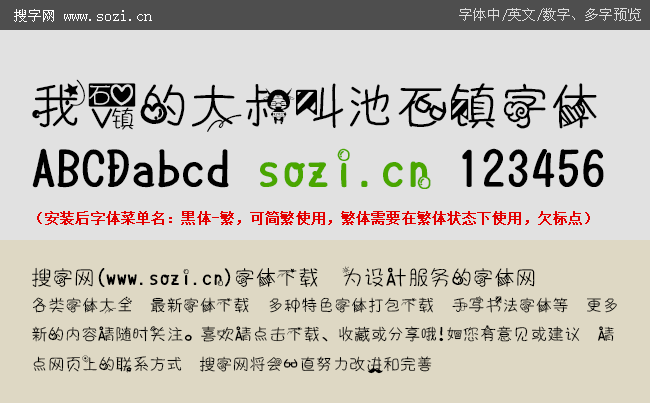
我愛的大叔叫池石鎮(zhèn)字體
搜字網(wǎng)給大家提供一款很卡通的手寫風(fēng)格手機中文字體下載。修改者將它命名為我愛的大叔叫池石鎮(zhèn)字體,這款手機字體是是仿照兒童手寫風(fēng)格的卡通手寫字體。并在字體筆畫間插入大量的卡通圖形,即有卡通字體的趣味性,又有手寫字體的藝術(shù)性,特別適合喜歡手機字體個性一些的朋友在手機上安裝使用。